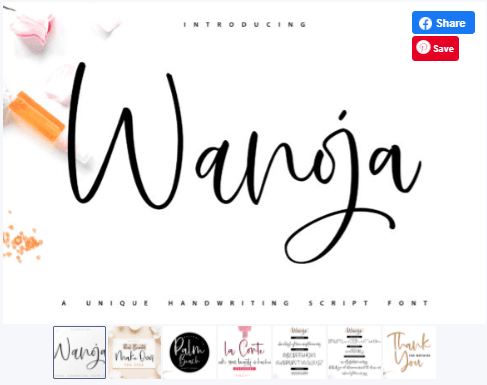
Wanoja Font
Wanoja - тонкий и стильный рукописный шрифт. Этот шрифт имеет кодировку PUA, что означает, что вы можете легко получить доступ ко всем глифам и росчеркам!
Влюбитесь в нее и доведите свои проекты до высочайшего уровня!